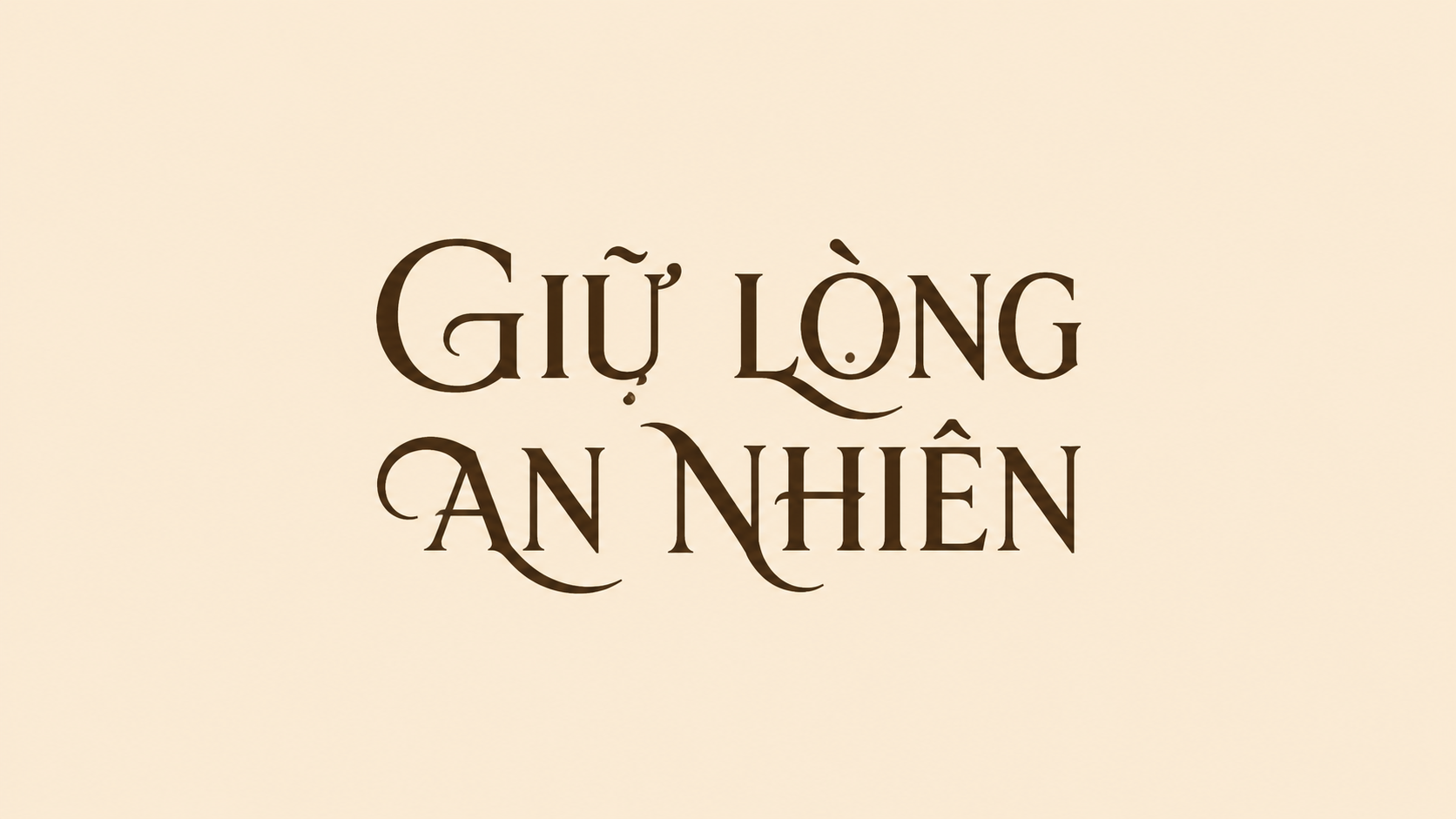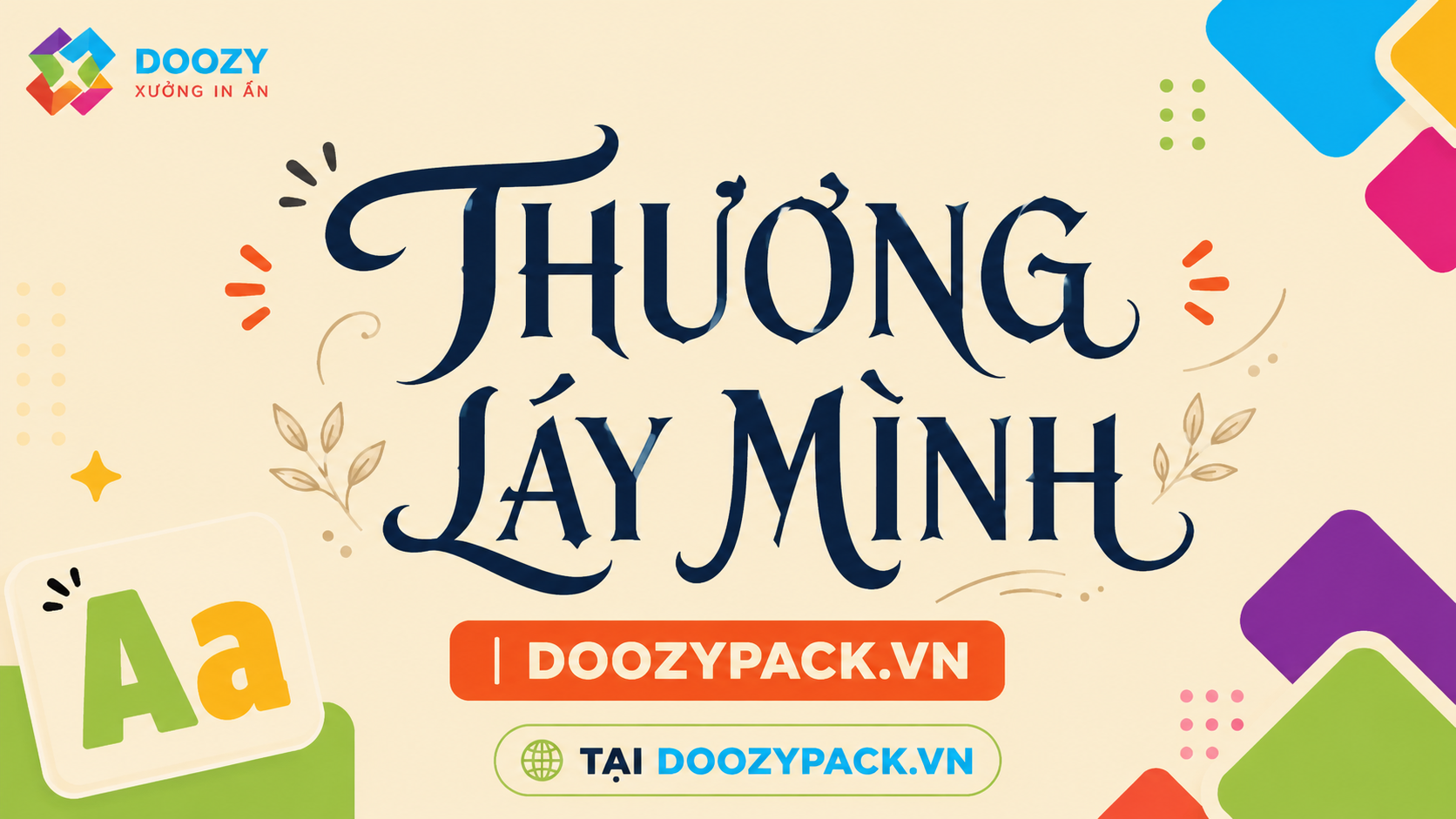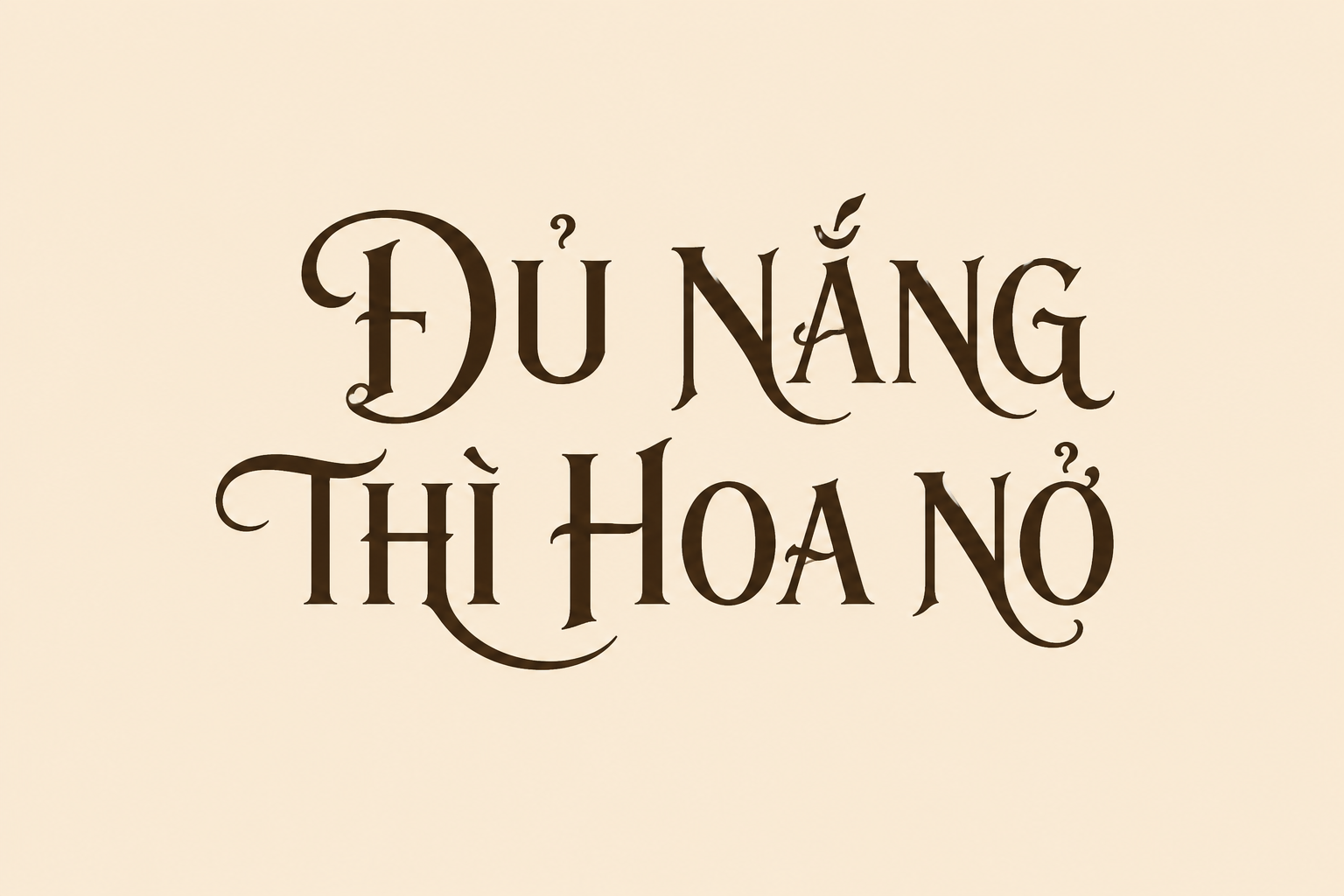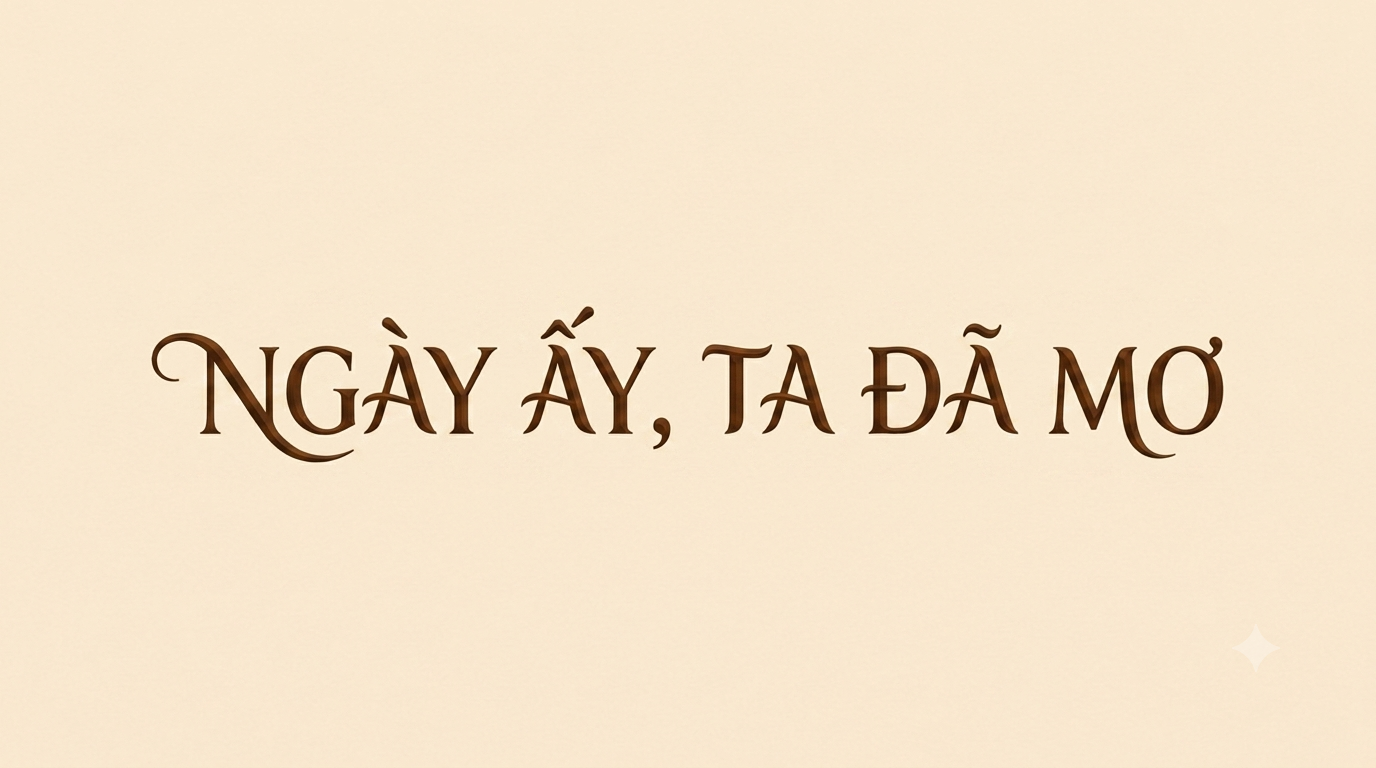
Font cổ trang Việt hóa Zahra là bộ phông chữ Brush Script mang đậm hơi thở của nghệ thuật thư pháp hiện đại, được thiết kế với những đường nét mô phỏng nét bút lông mạnh mẽ và đầy sự ngẫu hứng. Với cấu trúc chữ có độ biến thiên cao, kết hợp cùng hiệu ứng xước tự nhiên, Zahra là lựa chọn hoàn hảo để tái hiện không gian cổ xưa trong các bản thiết kế Poster, bìa sách hay bao bì quà tặng truyền thống. Doozypack.vn chia sẻ link tải font chữ cổ trang Việt hóa Zahra chuẩn, đảm bảo hiển thị trọn vẹn các dấu thanh tiếng Việt mà không phá vỡ cấu trúc thẩm mỹ của bộ font.
Đặc điểm thẩm mỹ của font chữ cổ trang Việt hóa Zahra
Zahra không chỉ đơn thuần là một kiểu chữ, nó là sự kết hợp giữa kỹ thuật đồ họa hiện đại và tinh thần hội họa cổ truyền.
Nét bút lông (brush) mạnh mẽ, phóng khoáng và đầy nội lực
Đặc trưng lớn nhất của Zahra chính là những nhát bút dứt khoát, tạo cảm giác như được viết bởi một nghệ nhân thư pháp dày dạn kinh nghiệm. Các nét chữ có sự chuyển đổi linh hoạt từ những mảng đậm chắc khỏe đến các nét thanh mảnh uốn lượn, mang lại nhịp điệu thị giác sống động và lôi cuốn cho mọi tiêu đề thiết kế.
Hiệu ứng xước và mực loang tự nhiên tạo vẻ đẹp hoài niệm
Font chữ Việt hóa cổ trang Zahra gây ấn tượng nhờ các chi tiết xước giả lập mực tàu trên bề mặt giấy thô ráp. Những khoảng hở nhỏ li ti trong nét chữ không chỉ tạo chiều sâu mà còn mang lại cảm giác cổ kính, phong trần, rất phù hợp cho các dự án mang tính lịch sử, kiếm hiệp hoặc các sản phẩm có nguồn gốc từ thiên nhiên.
Ứng dụng của font chữ Việt hóa cổ trang Zahra trong thiết kế bao bì
Tại Doozypack.vn, font Zahra thường xuyên được lựa chọn để nâng tầm giá trị cho các ấn phẩm bao bì mang phong cách truyền thống:
- Hộp quà Trung thu và quà Tết: Những từ khóa như “Nguyệt Viên”, “An Khang” hay “Phúc Lộc” khi sử dụng font Zahra trên nắp hộp giấy giúp tạo nên vẻ đẹp sang trọng, uy nghi theo lối cung đình.
- Tem nhãn sản phẩm truyền thống: Rất phù hợp cho nhãn rượu thủ công, trà cổ thụ hoặc thực phẩm organic, giúp khách hàng cảm nhận được giá trị thời gian và sự tỉ mỉ trong từng sản phẩm.
- Ấn phẩm truyền thông sự kiện: Poster phim cổ trang, thiệp mời sự kiện văn hóa hoặc các thiết kế Typography cho mạng xã hội hướng tới chủ đề hoài cổ.
03 Lưu ý kỹ thuật khi in ấn font nghệ thuật Zahra tại Doozypack.vn
Việc đưa một bộ font có nhiều chi tiết xước và nét mảnh như Zahra lên chất liệu giấy thực tế đòi hỏi designer cần lưu ý một số vấn đề kỹ thuật tại xưởng in:
- Hạn chế ép kim (Hot Stamping) chi tiết quá nhỏ: Các nét xước li ti của Zahra có thể gây khó khăn khi làm khuôn ép kim nếu kích thước chữ quá bé. Để đạt độ thẩm mỹ cao nhất, bạn nên yêu cầu kỹ thuật viên “dọn” bớt các nét xước nhỏ hoặc in lụa thay vì ép kim nếu chữ có size dưới 24pt.
- Lựa chọn chất liệu giấy phù hợp: Font Zahra sẽ phát huy tối đa vẻ đẹp khi in trên giấy mỹ thuật có vân nhám hoặc giấy Kraft. Bề mặt giấy có độ mộc sẽ cộng hưởng với nét bút lông tạo nên hiệu ứng thị giác cực kỳ ấn tượng.